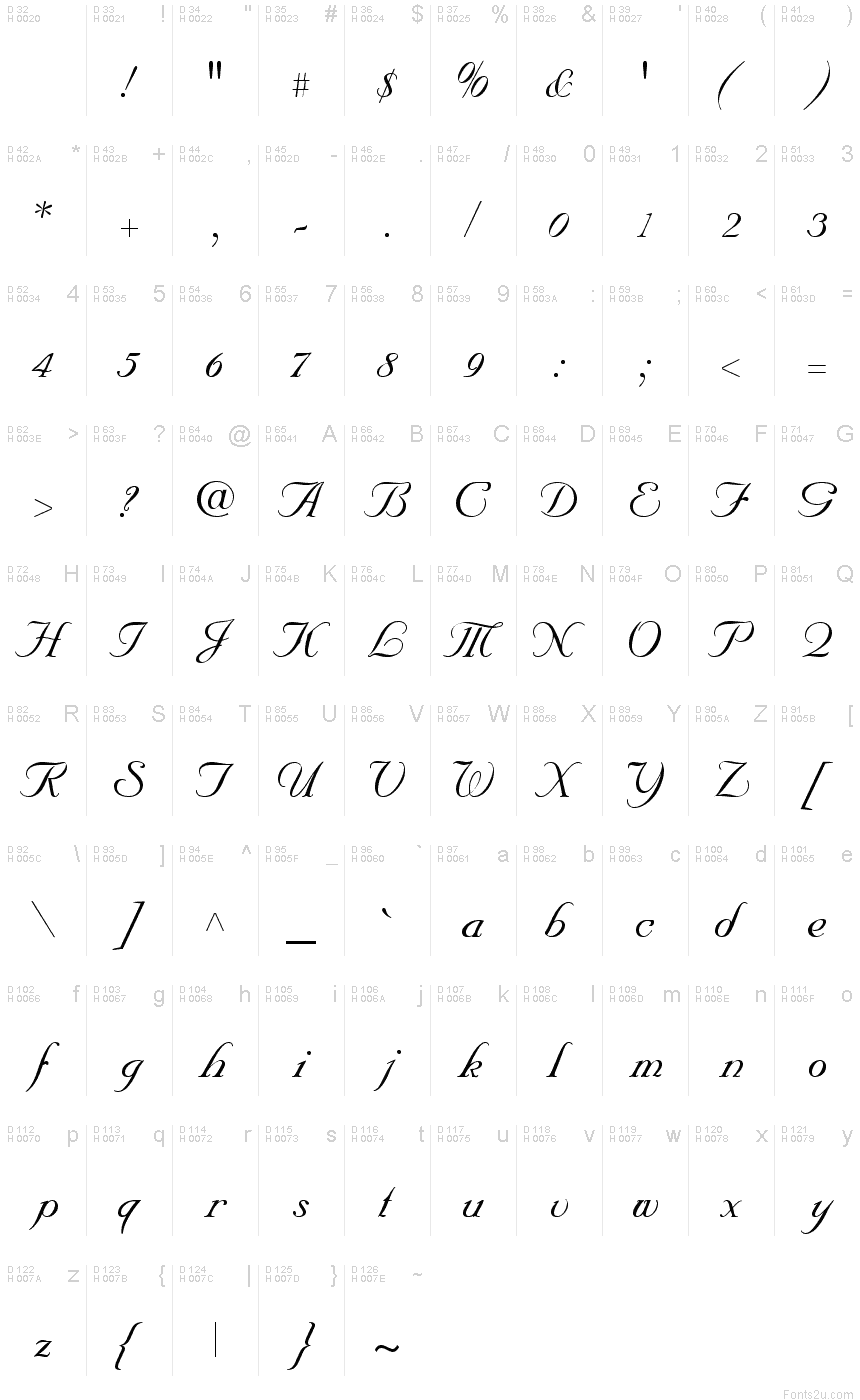
Nuncio Regular
Nuncio to bezpłatny krój kaligraficzny, którego zamaszyste linie początkowe i zwężające się krzywizny nadają literom liturgiczny, rękopiśmienny rytm. Projekt płynnie przechodzi od szerokich, ciemnych zakrętów do delikatnych, ostrych zakończeń, dzięki czemu kreska sprawia wrażenie napisanej szeroką stalówką, a nie tylko pochylonej dla efektu.
To sprawia, że Nuncio jest naturalnym wyborem dla biuletynów kościelnych, papeterii ślubnej, tytułów książek, nagłówków certyfikatów oraz brandingu win czy produktów z tradycją. Krótkie napisy wyglądają szczególnie przekonująco, gdy długie, początkowe zawijasy i miękko wygięte krzywizny okalają słowa, nadając im formalny, starodawny charakter.